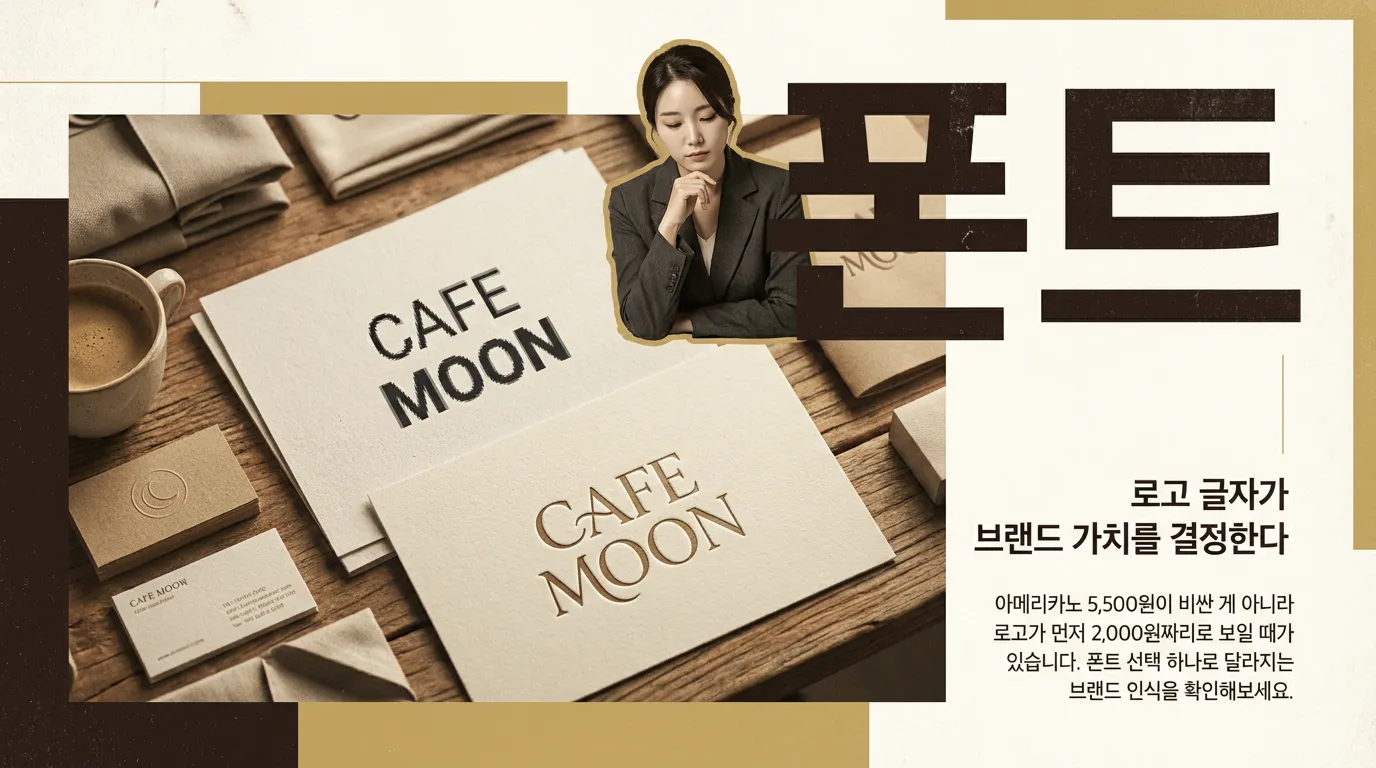
카페 로고 폰트 7가지 함정: 아메리카노 가격까지 싸 보이게 만드는 글자
카페 로고 폰트가 메뉴 가격 인식과 브랜드 포지션을 어떻게 바꾸는지, 비싸 보이는 서체와 피해야 할 서체를 실무 기준으로 정리했습니다.
아메리카노 5,500원이 비싼 게 아니라, 로고 글자가 먼저 2,000원짜리처럼 보일 때가 있습니다.
손님은 왜 메뉴판 보기 전에 가격대를 짐작할까요?
사장님, 손님은 원두 설명보다 로고를 먼저 봅니다. 간판, 컵, 영수증, 배달 썸네일에 반복되는 글자 모양이 “여기는 저가형인지, 동네 감성인지, 스페셜티인지”를 먼저 말해요.
공정거래위원회가 발표한 2025년 가맹사업 현황에서도 커피 업종은 가맹점 수와 평균 매출이 함께 늘어난 업종으로 언급됩니다. 시장이 커졌다는 말은, 동시에 비슷한 카페가 더 많아졌다는 뜻입니다. 그래서 폰트는 예쁜 장식이 아니라 가격표 앞에 서는 첫 번째 포지셔닝입니다. (news.seoul.go.kr)
비싸 보이는 카페 로고 폰트는 무엇이 다를까요?
저라면 세 가지를 먼저 봅니다. 획의 대비, 글자 사이의 숨, 그리고 끝 처리입니다. 얇고 굵은 차이가 분명한 세리프는 디저트·티룸·로스터리 카페에 어울립니다. 반대로 군더더기 없는 산세리프는 브루잉바나 모던한 테이크아웃 카페에 맞습니다.
흥미로운 연구도 있습니다. 브랜드명이 대문자로 보일 때 프리미엄 인식이 달라질 수 있다는 실험 연구가 있었고, 제품 형태와 서체가 어울리면 브랜드 미감과 가격 기대치가 올라간다는 연구도 있습니다. 결국 글자는 혼자 잘나면 안 됩니다. 공간, 메뉴 가격, 컵 질감과 같은 편이어야 비싸 보입니다. (sciencedirect.com)
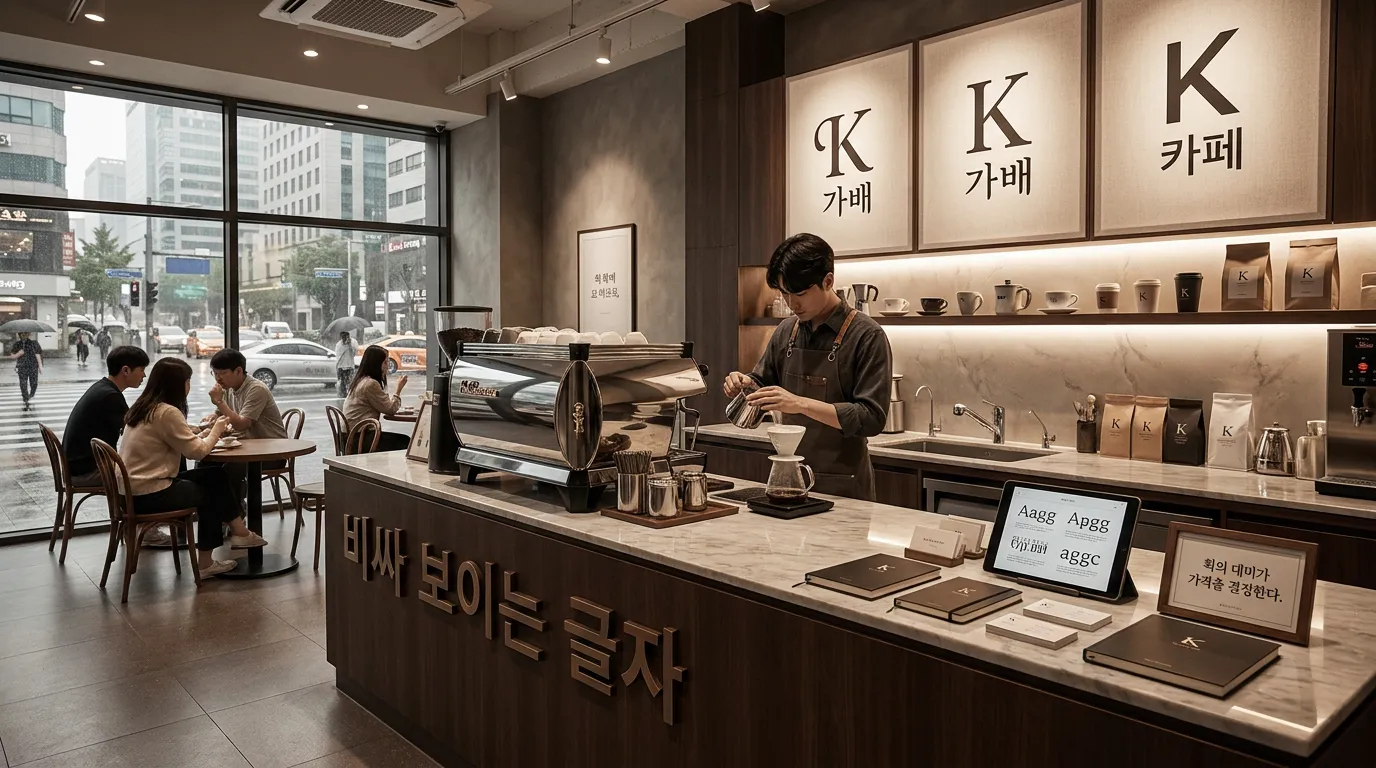
피해야 할 서체 7가지는 어디서 티가 날까요?
첫째, 너무 얇은 감성 손글씨. 멀리서 안 읽히고 개인 공방처럼 보입니다. 둘째, 동글동글한 무료 고딕. 친근하지만 객단가를 올리기 어렵습니다. 셋째, 붓글씨 캘리. 커피보다 전통찻집 인상이 강해집니다.
넷째, 배달앱 배너 같은 굵은 고딕. 빠르고 싸게 보입니다. 다섯째, 장식 많은 빈티지 서체. 오래된 느낌과 낡은 느낌은 다릅니다. 여섯째, 폭이 지나치게 좁은 콘덴스드. 작은 컵 스티커에서 답답합니다. 일곱째, 라이선스가 애매한 무료 폰트. 한국저작권위원회 상담 사례에서도 무료 폰트는 이용 범위가 개인·비상업으로 제한된 경우가 있어 민사상 문제가 생길 수 있다고 설명합니다. (copyright.or.kr)
그럼 어떤 기준으로 고르면 실패가 줄어들까요?
폰트 이름부터 고르지 마세요. 먼저 “우리 카페에서 가장 비싸게 팔 메뉴”를 적어보세요. 7,000원 라떼인지, 8,500원 디저트인지, 원두 판매인지에 따라 글자의 체급이 달라집니다.
그다음 로고를 세 군데에 올려보면 됩니다. 정면 간판, 8oz 컵, 인스타 프로필. 여기서 한 번이라도 싸 보이면 탈락입니다. 마크에서 카페 로고를 잡을 때도 화면 속 예쁨보다 실제 적용 크기에서 먼저 걸러냅니다. 로고는 확대 포스터가 아니라 매일 손님 손에 들리는 작은 컵에서 버텨야 하니까요.